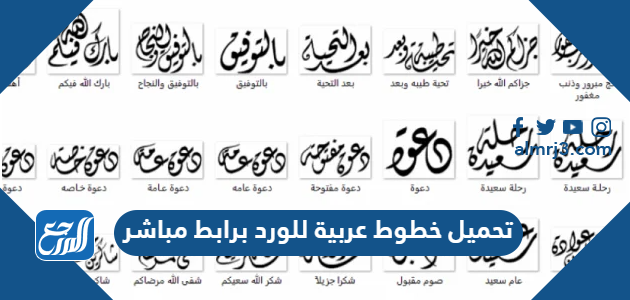
تحميل خطوط عربية للورد برابط مباشر 2026
تحميل خطوط عربية للورد برابط مباشر 2026 من أجل الكتابة بعدد من الأشكال والزخرفات المختلفة، حيث يرغب العديد من الكتّاب بالقيام بنقل أو تأليف مختلف أنواع النصوص، مما يتطلّب منهم عدد من أشكال الخطوط المختلفة للتمييز بين أنواع الكتابات المختلفة، مثل الاقتباسات، أو القصائد الشعرية، أو الآيات القرآنية، أو غيرها، ومن هذا المنطلق يهتم موقع المرجع تعريفنا على الطريقة التي يتم من خلالها تحميل عدد من الخطوط العربية والأجنبية المزخرفة التي تستخدم في الكتابة على برنامج الوورد.
يمكن الحصول على الخطوط العربية المزخرفة على تطبيق الوورد من خلال تثبيت ملف الخط على البرنامج، وتقدم العديد من المواقع الخطوط على شكل مجموعات من الخطوط بملفات مضغوطة، وتأتي أغلب هذه الخطوط بصيغة WinRAR أو ZIP أو Peazip، والمجموعة التي سنقدمها تحوي على الخطوط الأساسية الشهيرة مثل الديواني والثلث ورقعة، بالإضافة إلى عدد من الخطوط الحديثة الأكثر تداولًا بين المستخدمين، وتحوي هذه المجموعة على عدد كبير جدًا من الخطوط.
تحميل خطوط عربية للورد برابط مباشر 2026 مقال أوردنا فيه عدد من الخطوط العربية المتوافقة مع برنامج مايكروسوفت بصيغة TTF، حيث أننا قد قمنا بإدراج عدد من الروابط التي يمكن من خلالها تحميل حزم من الخطوط بما يزيد على 500 خط عربي، بالإضافة إلى عدد من الخطوط الأجنبية والعربية المزخرفة.